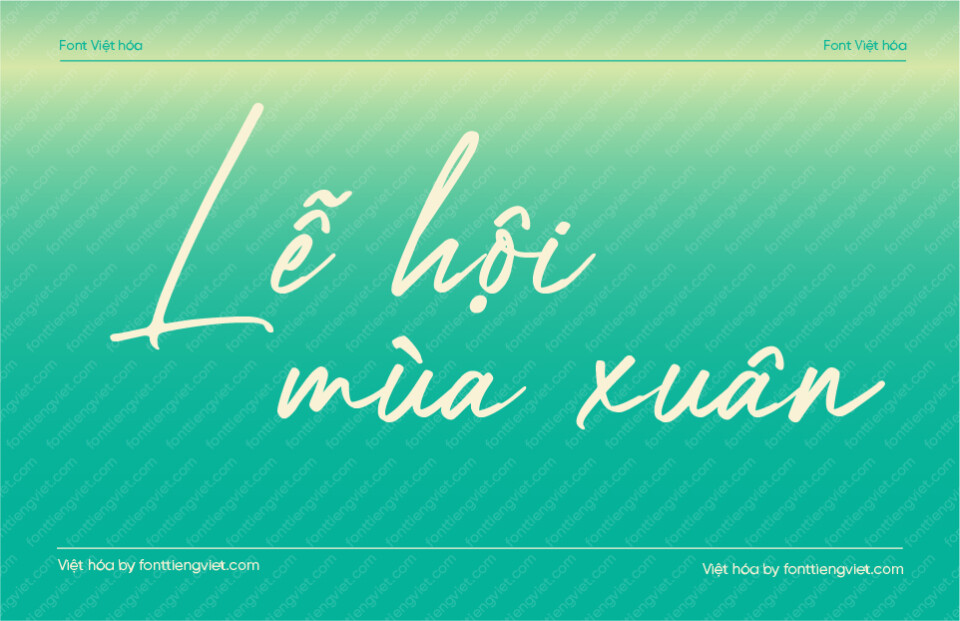
Font Việt hóa 1FTV VIP Alpha Brights – Sự lựa chọn hoàn hảo cho thiết kế giáo dục
Trong thế giới thiết kế đồ họa hiện đại, việc tìm kiếm một bộ Font Chữ vừa mang tính thẩm mỹ cao vừa hỗ trợ đầy đủ tiếng Việt là điều vô cùng quan trọng. Font Việt hóa 1FTV VIP Alpha Brights nổi lên như một giải pháp lý tưởng dành cho những người yêu thích phong cách trẻ trung và năng động. Đây là bộ font được tinh chỉnh kỹ lưỡng về dấu câu, giúp các nhà thiết kế tại Việt Nam dễ dàng ứng dụng vào nhiều loại sản phẩm khác nhau mà không lo lỗi hiển thị. Với các đường nét bo tròn thân thiện và độ dày vừa phải, bộ font này mang lại cảm giác dễ chịu cho người xem, đặc biệt phù hợp trong môi trường học đường.
Đặc điểm nổi bật của Font Việt hóa 1FTV VIP Alpha Brights
Bộ font này sở hữu cấu trúc ký tự rõ ràng, giúp tối ưu hóa khả năng đọc trên cả thiết bị số và ấn phẩm in ấn. Sự cân bằng giữa các nét chữ tạo nên một tổng thể hài hòa, giúp thông điệp truyền tải trở nên nổi bật hơn. Font Việt hóa 1FTV VIP Alpha Brights không chỉ dừng lại ở việc hỗ trợ gõ tiếng Việt chuẩn mà còn giữ nguyên được tinh thần sáng tạo của bản gốc, giúp các bạn học sinh và giáo viên tạo ra những bài giảng điện tử sinh động hay các dự án ngoại khóa ấn tượng.
Ứng dụng đa dạng trong học tập và đời sống
Nhờ phong cách hiện đại, font chữ này thường được sử dụng để thiết kế tiêu đề bài thuyết trình, làm thiệp chúc mừng hoặc trang trí báo tường. Khả năng tương thích tốt với các phần mềm thiết kế phổ biến giúp người dùng tiết kiệm thời gian chỉnh sửa thủ công.
Kết luận về bộ font Việt hóa chất lượng